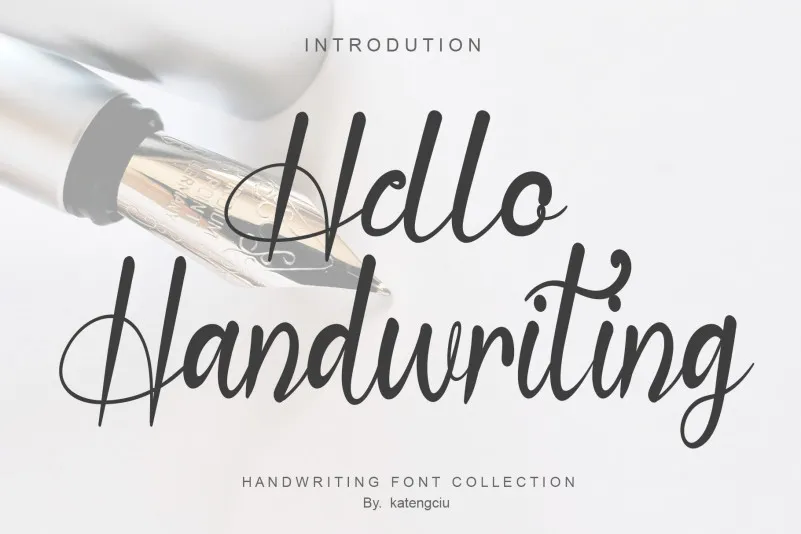
Hello Handwriting Font – Download Grátis
Esta é uma fonte escrita a mão delicada e elegante. Seus caracteres distintos e equilibrados fizeram desta fonte uma verdadeira obra prima. Perfeito para se apaixonar por sua versatilidade incrível, use-o para criar designs espectaculares! Este texto foi baseado na descrição original da fonte, mantendo a essência do estilo elegante e delicado sem usar traduções diretas ou inventar características fora da descrição fornecida.